在学生成长和学习的过程中,写字是必不可少的事情,而家长们对于学生写字这方面其实也是非常的重视,尤其是在字体上吃过亏的家长,会更加的注重学生的字体。
现在人们的生活条件都有了非常不错的改善,家长们能够给学生营造的教育条件也不一样了,要比以前真的是好太多了。
现在的学生可以说,只要她们想学习,不论是兴趣爱好还是学习知识,家长们都会尽量满足,毕竟现在的社会是多一个兴趣爱好,就可能多一个竞争优势和机遇。
而很多家长因为对学生的字体的重视,更是会在学生小的时候,就给学生报书法班,或者是让学生练习一些字体,就是希望学生能够写出一手漂亮的字。
“奶酪字体”在中小学盛行,可老师却并不喜欢
很多人其实对于奶酪字体并不是很了解,甚至有一些家长还不知道什么是奶酪字体。其实,这种字体是一种网红字体。
之前,在网络上经常会看到这样的字体,在网络上经常会看到这一样的字体,还会有很多的写作教程。
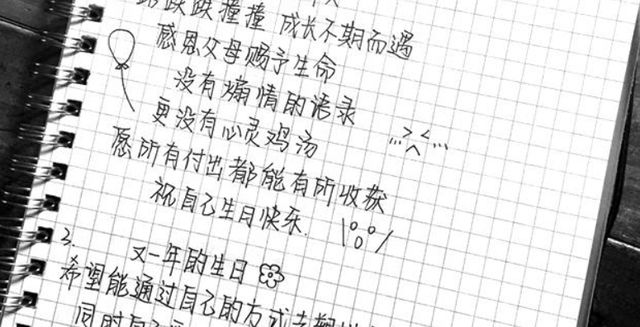
这种字体非常的简单,与传统的楷书相比,奶酪字体可以说是一个简写的过程,学生们比较好上手,所以,很多中小学生也是得起精髓,这种字体也就在中小学偷偷的盛行开来。
学生们偷偷地去练习,虽然这个字体,如果字数不是很多的话,看上去还是比较公正好看的,但是如果真正要是答题的话,整个卷面都是这样的字体。
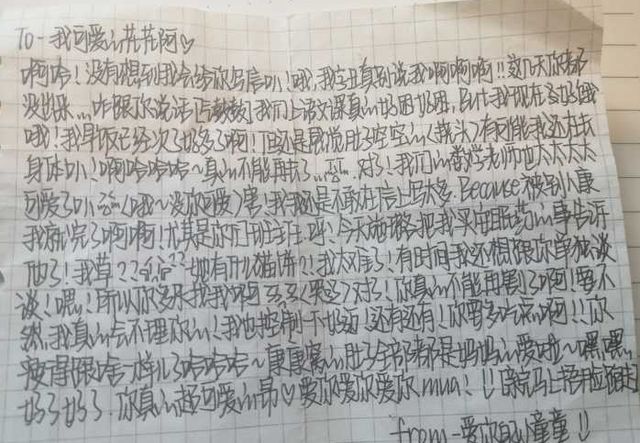
那么对于老师来讲,可能就是一个灾难了,老师看到这样的字体后会眉头紧锁,他们并不喜欢这样的字体,所以,如果学生在考试的时候用这样的字体,那么就要小心考试卷面被扣分了。
毕竟,对于老师们而言,还是喜欢那种横平竖直,而且非常工整的字体,这样的字体才能更受老师们的欢心。
所以,中小学生的家长们,如果自己的学生还在写奶酪字体的话,一定要及时地去更正,否则最好影响的还是学生。
考试时字体不一样要写得多漂亮,但是工整程度真的很重要
字体得更好程度是很重要的一个事情,不过,在考试的时候,其实老师看重的更加是学生的试卷整洁程度。
学生们即使字体并不是很漂亮,但是,能够用心答题,而且还能够是卷面工整的话,那么,一般分数就不会低。
毕竟,老师们一般在阅卷的时候都是要看很多卷纸的,如果字体不漂亮,而且卷面还不工整的话,那么老师看到这样的卷纸就会感到非常的疲劳。
这样的话,老师在阅卷的时候,可能卷面分数就不是很好了,学生们在这一点上要注意,即使考上的时候字体不是很好看,但是也要非常工整地去书写。
这样阅卷老师才不至于给大家扣卷面分数,毕竟,在重要的考试的时候,可能少一分或者两分都会给大家带来不一样的结果。
学生在练字的过程中,家长要督促学生做好这几点
1、练字要选择楷书,不要去学习一些比较花哨的字体
学生在练习写字的时候,一定要注意,千万要选择楷书,因为楷书对于学生来讲,是练字的基础,而且更加的适合大众的审美,所以,家长要督促学生在练字的时候要以楷书为标准,不要去学习一些比较花哨的字体。
2、练字时一笔一划都要用心书写,要把握好基础
对于中小学生而言,其实学习的兴趣并不是很大,所以,很多时候很难静下心来,但是,练习写字的时候,家长必须要让学生静下心来,如果心不静,那么字也就很难写好,所以,家长要督促学生把握好基础。
3、练字时要心无旁骛,不能被外物所打扰和诱惑
学生在练习写字的时候,一定要做到心无旁骛,要想的就是怎样将字写好,在练习写字的时候,家长一定要做好督促的作用,要让学生不被外物所打扰和诱惑,这样才能写出工整美观的字体。
学生们在练习字体的时候,一定要选好字体,否则,练习一个不好的字体,对于学生而言,真的是吃大亏的,所以,家长一定要做好督促的作用,千万不要让学生在字体上吃亏。一定要让学生学习正规的字体,这样才能得到大家的认可,在考试的时候才能得到老师的欣赏。